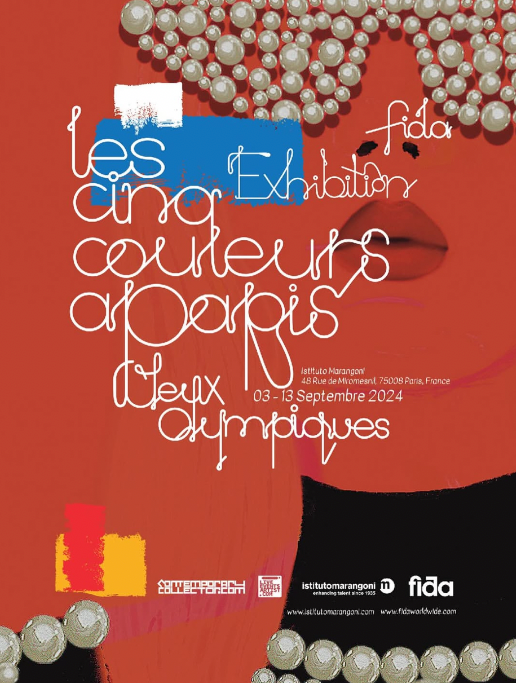
Verschnörkelte Schreibschrift auf französischem Fashion-Olympics-Plakat 2024
Gesucht wird die Headlineschrift des Plakats in Frankreich von 2024 Auftraggeber vermutlich fidaworldwide.com.